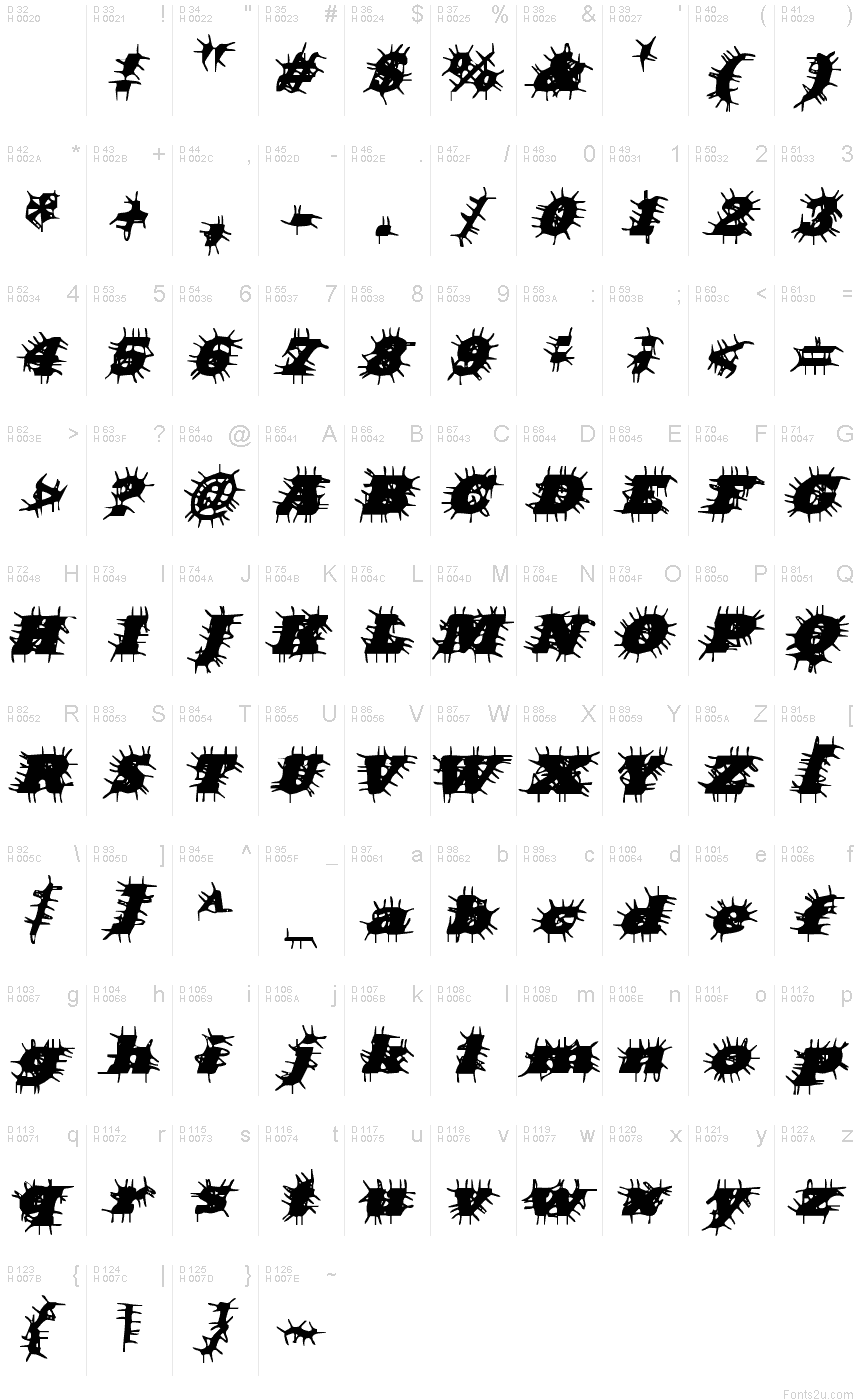
Bad Hair Day od Phillipa Andradea je volně šiřitelné, zkreslené titulkové písmo, které vypadá, jako by se právě vydrápalo z toho nejchaotičtějšího skicáře. Každé písmeno je poseté ostrými hroty a šmouhami inkoustu – jako divoké vlasy trčící na všechny strany, což textu dodává roztřesenou, drsnou siluetu. Působí to jako výkřik načmáraný fixou: nepravidelné, a přesto překvapivě kompaktní, když se použije v krátkých úsecích nebo výrazných nadpisech.
S písmem Bad Hair Day okamžitě dodáte plakátům, halloweenským letákům, hororovým knižním obálkám, fanzinům, obalům alb nebo drsnému merchi pořádnou dávku chaosu. Nejlépe vynikne ve větších velikostech, kde naplno zazáří jeho inkoustové, roztřepené hrany. Pro hlavní text ho skvěle doplníte jednoduchým bezpatkovým písmem. Stačí držet slova krátká a úderná, nechat písmena dýchat pomocí většího prostrkání, a získáte vizuální výkřik, na který nikdo nezapomene.